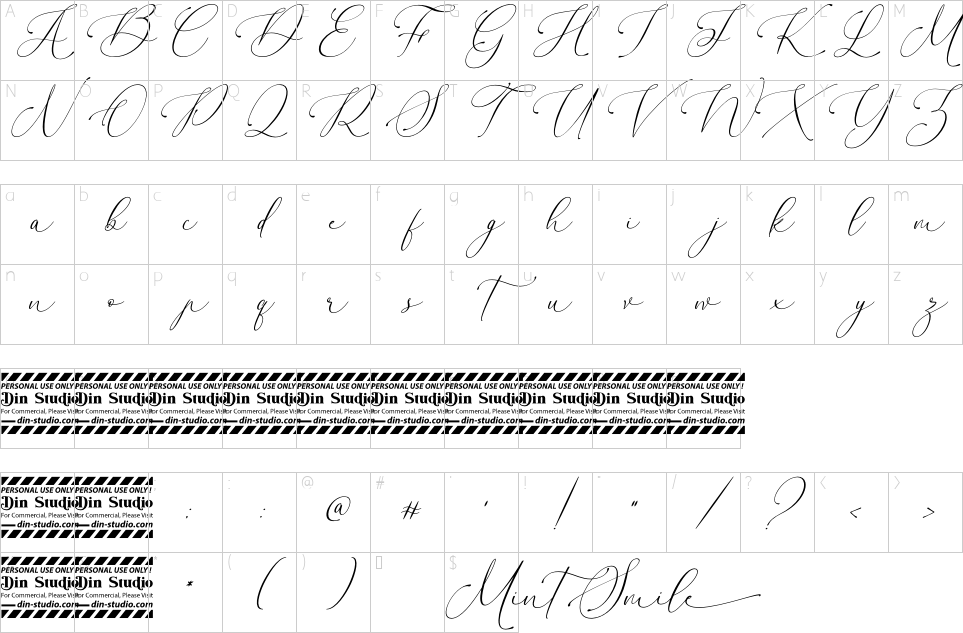
A Mint Smile é uma fonte gratuita que oferece uma experiência visual leve e descontraída, perfeita para estilos gráficos que desejam um toque amigável e descontraído. Desenvolvida pelo Din Studio, esta fonte pode ser facilmente integrada em projetos de design para proporcionar um visual alegre e agradável, ideal para aplicativos de mensagens, sites pessoais ou qualquer projeto onde um tom leve e descontraído seja desejado. Com suas linhas levemente onduladas e sua expressão alegre, a Mint Smile é uma escolha inteligente para qualquer projeto que deseje um toque alegre e descontraído, sem comprometer a legibilidade e a estilização. Com mais de 700 downloads, a Mint Smile é uma fonte confiável e altamente recomendada pelos designers.